字由 x loyotype 中文字体设计精研班报名开启!
文字作为信息传达的载体,字型的选择是重中之中,无论是方俊的、圆柔的、厚重的还是清新的……不同的字型带来的视觉感受完全不同。每一位设计师都应该做到深入的理解字体、灵活的应用字体、轻松的设计字体,从而营造独特的、新颖的视觉感受。
因此,字由联合loyotype,第①期中文字体设计精研班重磅推出。
Loyotype中文字体设计精研班始终立足鱼渔兼授,以赛养学,价值转化的核心理念。我们深知,教育的真谛不仅在于知识的传授,更在于能力的培养与价值的实现。
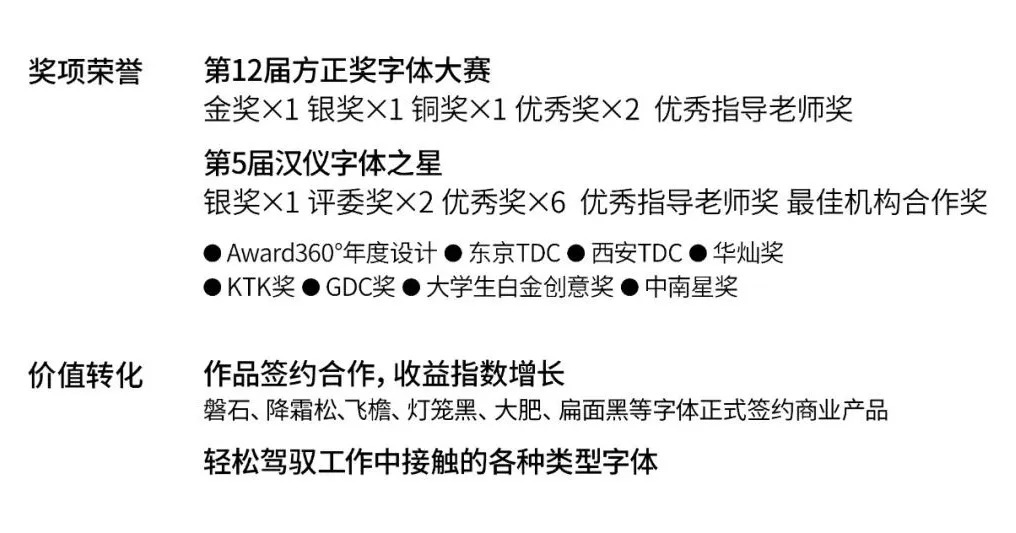
课程优势
◎ 成果斐然: 学员在国内外字体设计比赛中屡获殊荣 ◎价值转化: 重视作品转化,毕业作品有机会签约字由字体产品 ◎以赛养学: 指导学员参与国内外比赛,快速提升设计水平 ◎顶尖师资: 一线知名设计师倾囊相授,链接机会,共享资源 ◎小班教学: 小班精研,确保每位学员获得关注与指导
课程大纲
第一部分 基础夯实系统
这些原理编织的系统是解决字型好用的必经途径,也是常销产品的根本所在。训练营版块强化理论与实践结合,做到活学活用。
1 字体的价值|商业案例分享+定位
2 曲线与布点|篆书+隶书+楷书实操
3 曲线与布点|行书+草书+拉丁实操
4 灰度与布白
5 大小与重心
6 阴阳与粗细
7 视错与方向
8 基础课总结 | 作业修改实操
◎2-7课设置作业
第二部分 造型与审美系统
字体是功能、设计、美学与用户导向的综合产物。笔画造型是外在形式美,结体是内在灵魂,结体创新是字体设计毕生的追求。
9 笔画造型原则与生发
10 结构造型原则与生发
◎9-10课设置作业
第三部分 商业与产品系统
从用户与市场的角度出发,与字由字体设计师一同,结合字由点字库等商业字库实例,为学员进行商业字型的定位、产品、参赛等指导,实现设计成果多重转化。
11 商业字型定位与设计 ◎设置作业
12 字库产品商业定位 ◎设置作业
13 参赛作品打造 ◎指导参赛字稿
14 三大系统总结 ◎结课作业点评
综上,从夯实字体的基本要素,到审美与造型建立后的作品诞生,再到产品思维和参赛属性叠加的定位与打磨。这些知识的系统串联是课程的核心所在,也是我们工作多年研究和实践的有效方法。
往期精研班部分学员作品
《磐石》 @GBIN
第5届汉仪字体之星 中文专业组优秀奖 已签约产品
《飞檐隶书》 @严谨
第5届汉仪字体之星 中文学生组优秀奖 已签约产品
《降霜松》 @渔
第5届汉仪字体之星 中文学生组评委奖 已签约产品